Love Cursive STL Wall Art
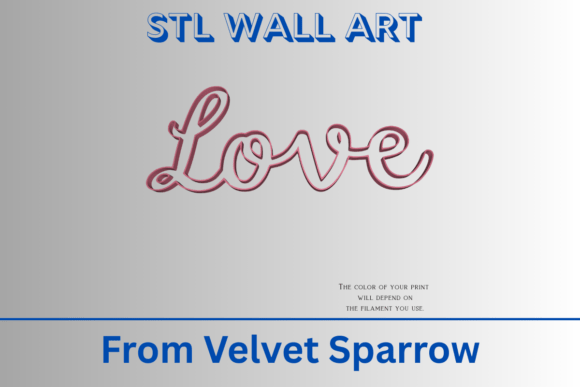
Trouver les bons éléments de conception peut être un défi, mais Love Cursive STL Wall Art propose une collection exceptionnelle qui rehausse instantanément votre travail.
Conçu avec précision, Love Cursive STL Wall Art offre des vecteurs nets, une typographie fluide et une licence commerciale pour une tranquillité d'esprit.